元号は変わりますが、「平成」って書類とかで書く機会多いと思います。
「平成」のきれいな書き方
「平成」の見本
こんな感じに書いてみました。
「平成」の重要ポイント
それぞれの文字の「強調する画」を確認しましょう。
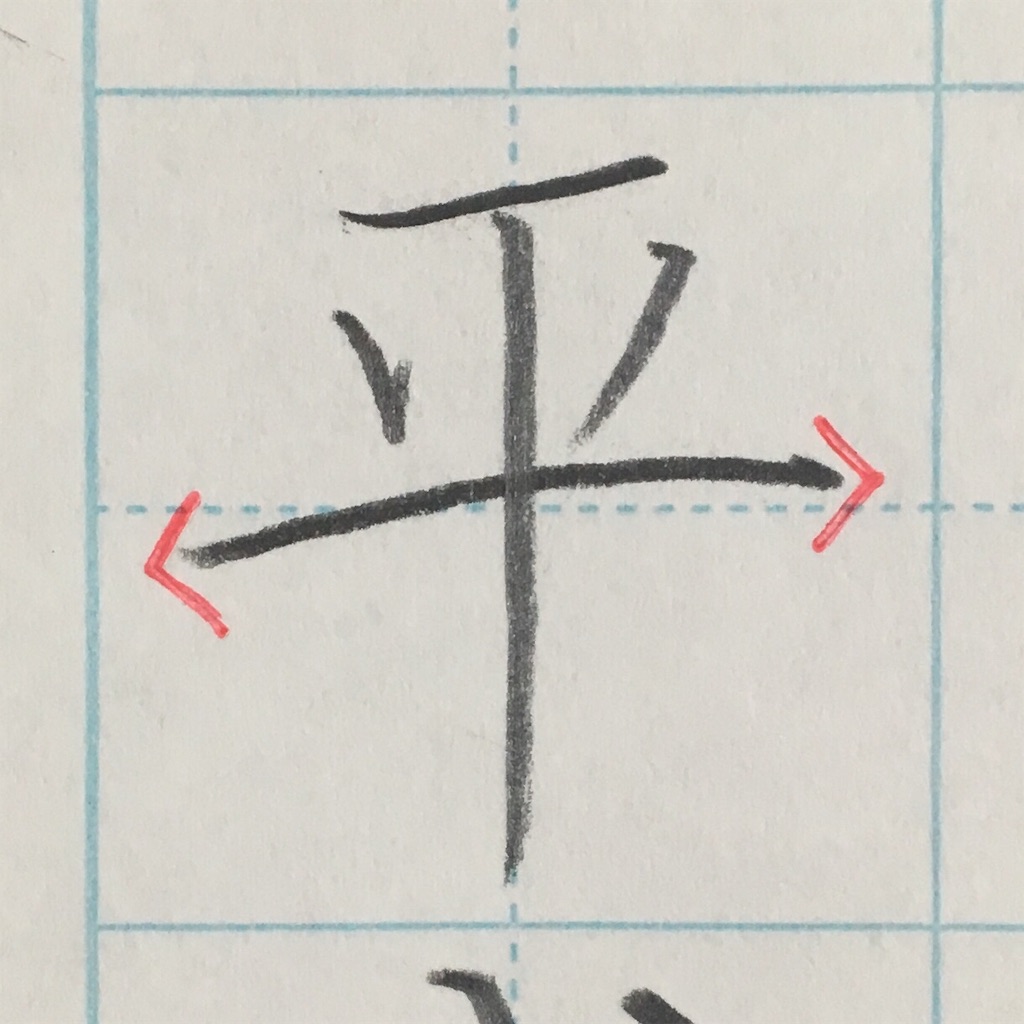
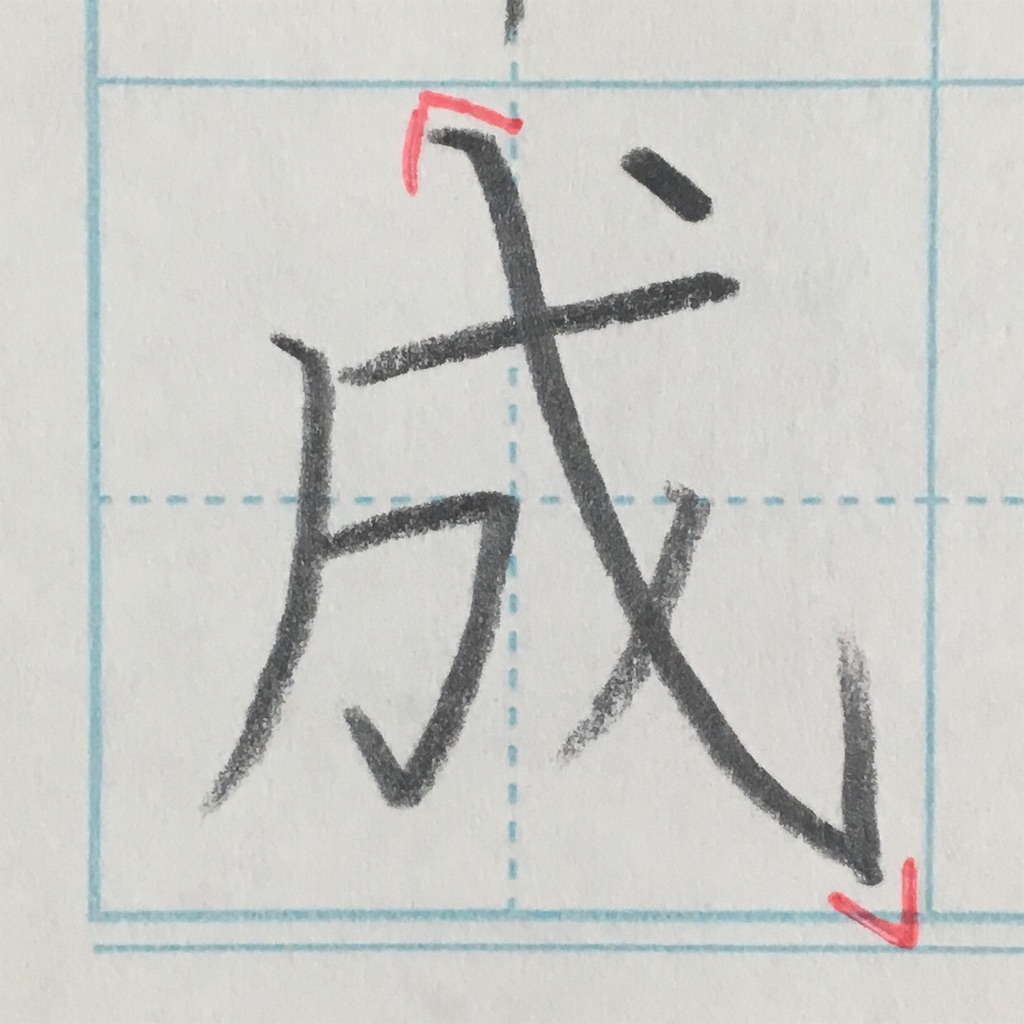
この2画です。
「一画強調」というのが文字を書く上での基本となります。
出すところは出す、引っ込めるところは引っ込める。
線の長さは、「なんとなく」書いてしまいがちですが、バランスを取るためには、それぞれの画の長さ(位置関係)を覚えておく必要があります。
「平」の細かいポイント
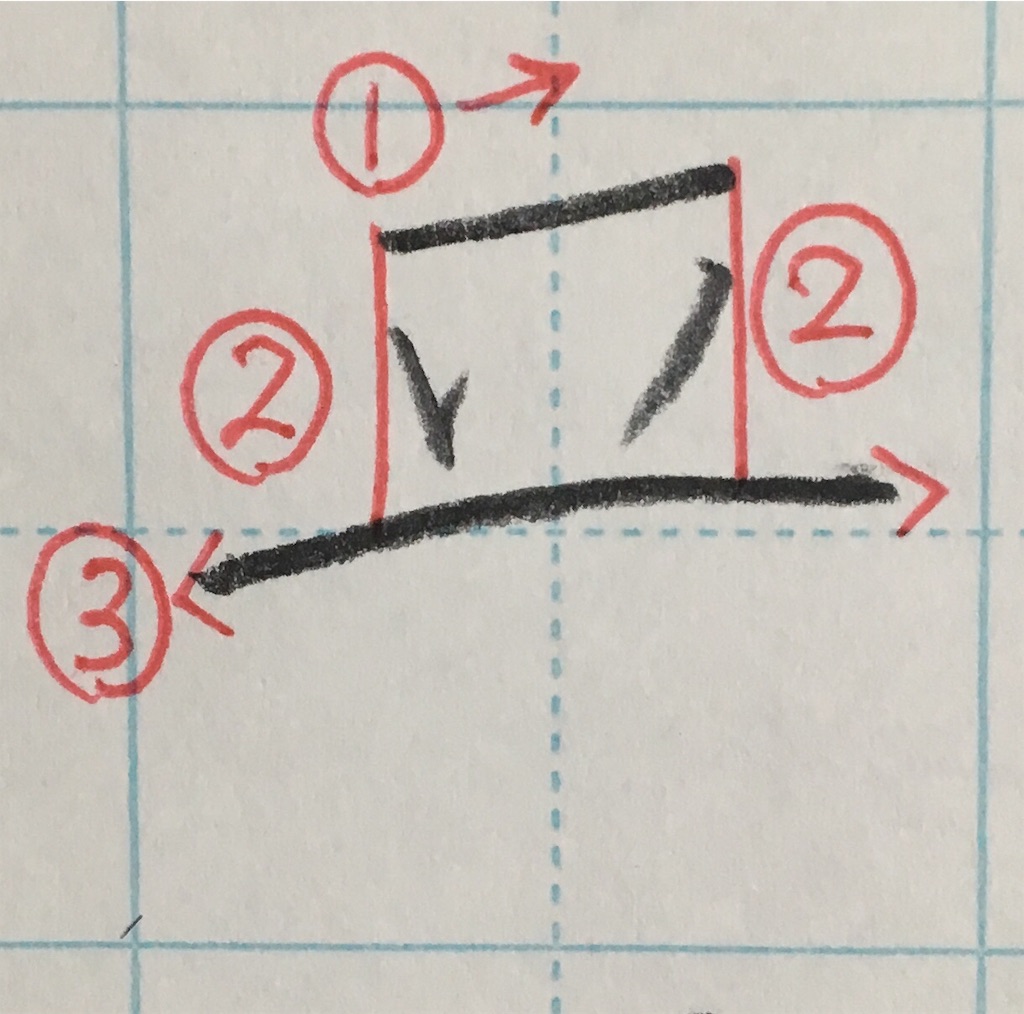
①短く、右上がりに。中央にしっかりと収めましょう。(長さの目安は、書くスペースの半分くらい。)
➁2画目と3画目は、1画目よりも外に出ないように。それぞれ、1画目の端からスタートすると良いです。
➂長く強調、少し反ると◎
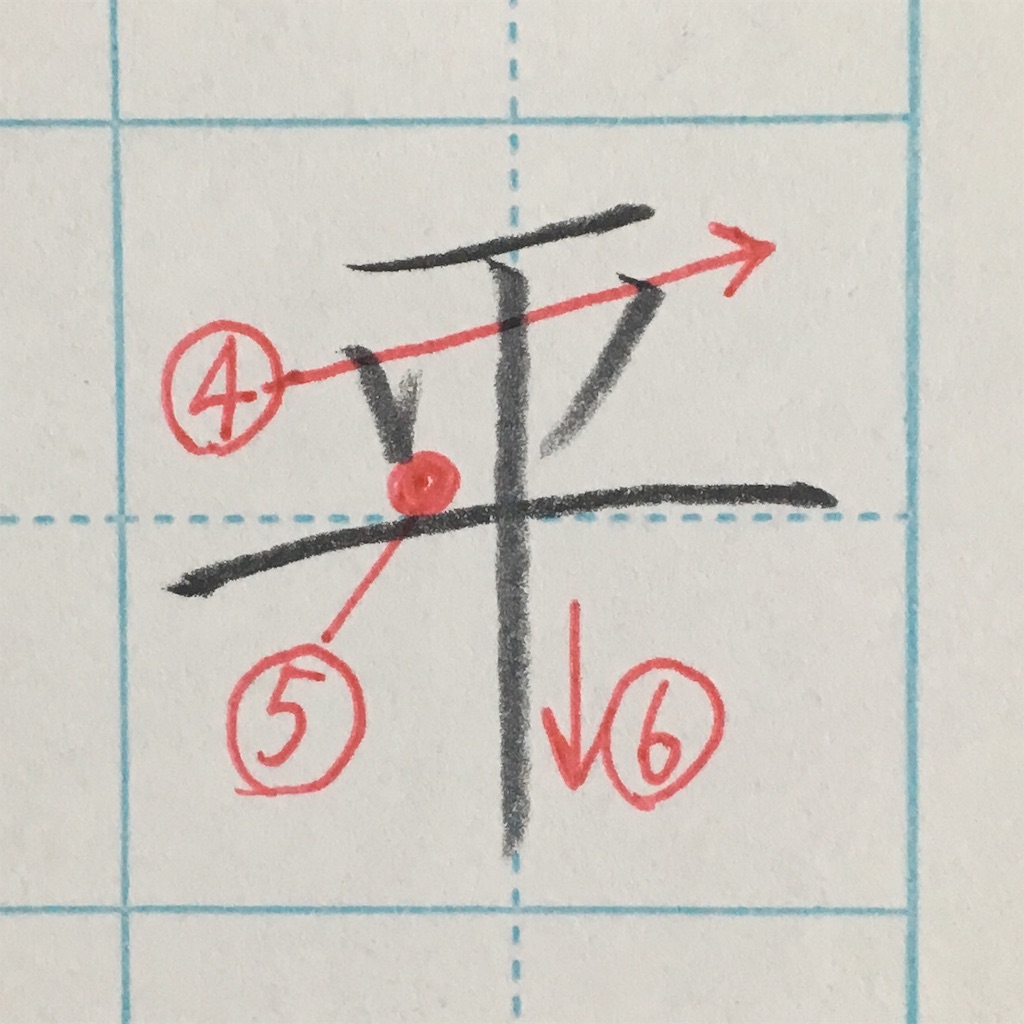
➃2・3画目も横画に合わせて右上がりの関係にしましょう。
➄ここは、くっつけない。
➅最終画は、中心に、まっすぐ。最後はスっと払います。
「成」の細かいポイント
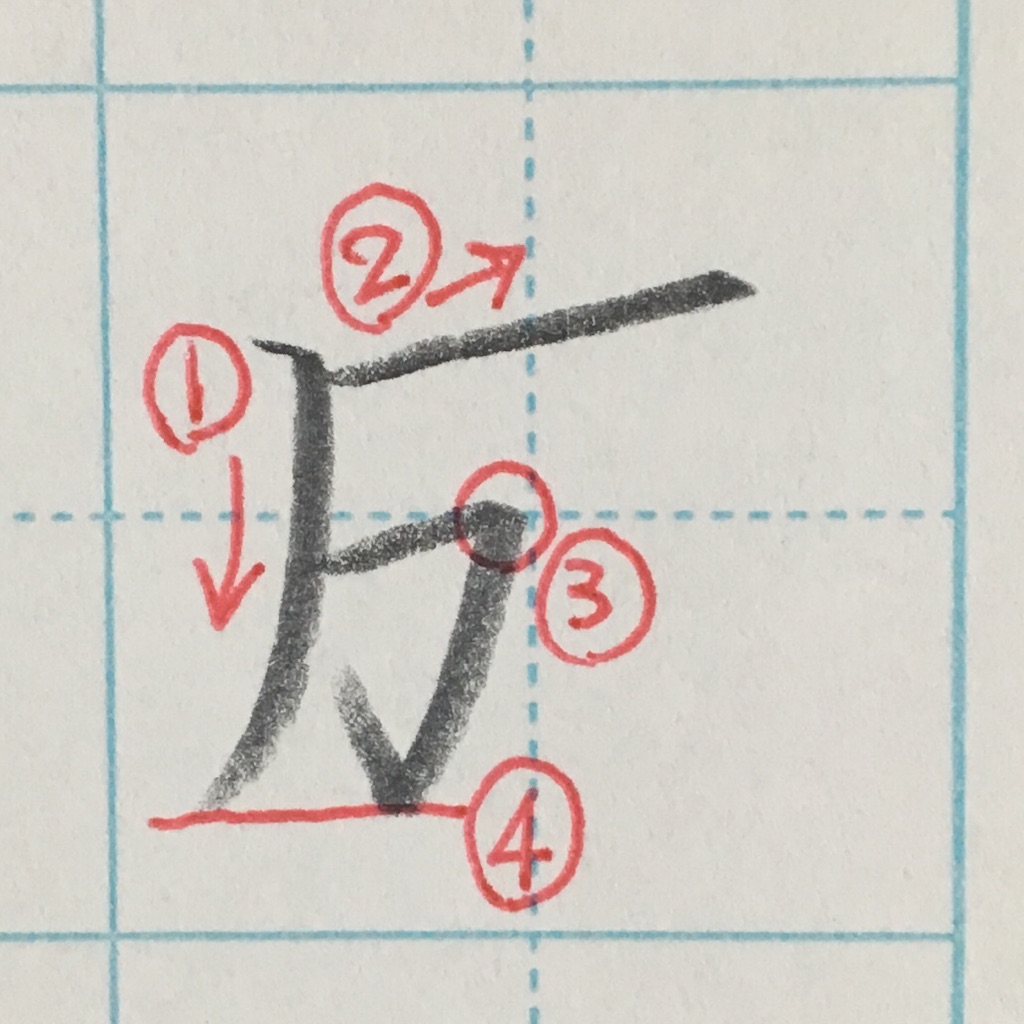
①1画目は、縦画からですよ!横画から書いてる方、いませんか? いきなり斜めにするのではなく、半分くらいまでまっすぐに。そこから緩やかに曲げて払っていきます。
➁右上がりに。
➂角がちょうど中央になります。
➃下は揃えます。
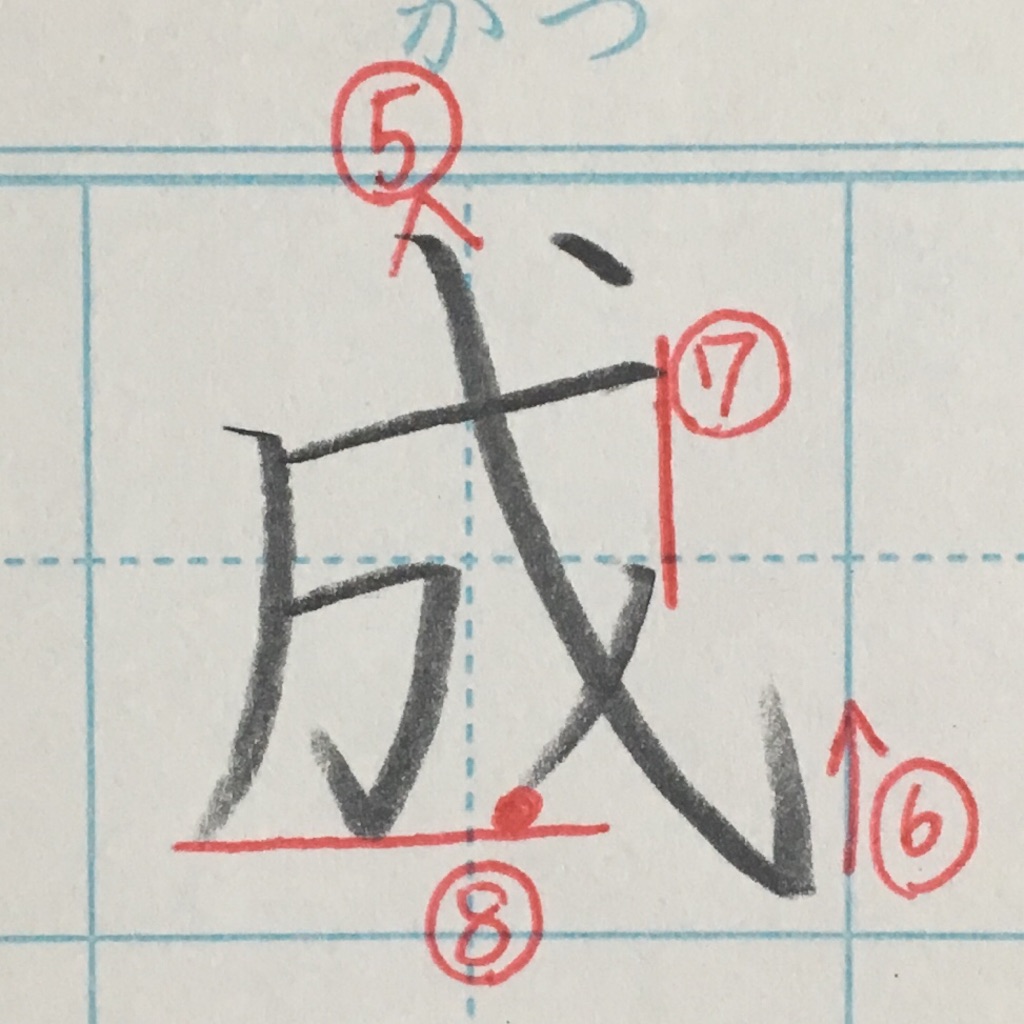
➄上にしっかりと突き出す。少し反って、思い切って右下のスペースに入れていきます。
➅ハネは上に向けて。大きく。
⑦2画目と5画目は揃えます。(これも、4画目を強調させるための大切なポイントです。)
⑧ここは少し余白を作って。
最後に「てん」の位置。
2画目と4画目を基準としたスペースの中に入れます。ぎりぎり右端を狙って、斜め45°。
…完成!!